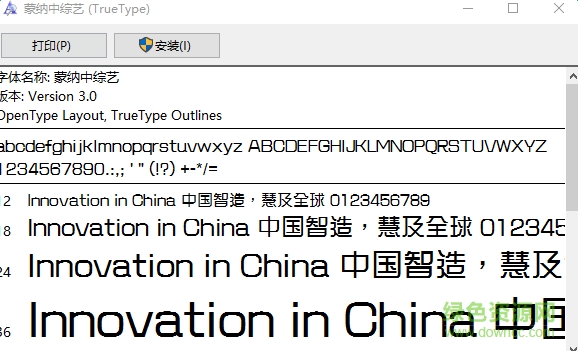
蒙納中綜藝字體是蒙納字庫中很實(shí)用的一款電腦字體,這款字體寫出來的字是很好看的,工整、大氣、美觀,可以用于很多方面,如果大家喜歡這款字體可以隨時(shí)來綠色資源網(wǎng)下載。
蒙納中綜藝字體是一款很不錯(cuò)的電腦字體,不僅實(shí)用性強(qiáng),而且字形美觀,用于書本印刷、藝術(shù)設(shè)計(jì)都是很不錯(cuò)的,歡迎大家來綠色資源網(wǎng)下載。